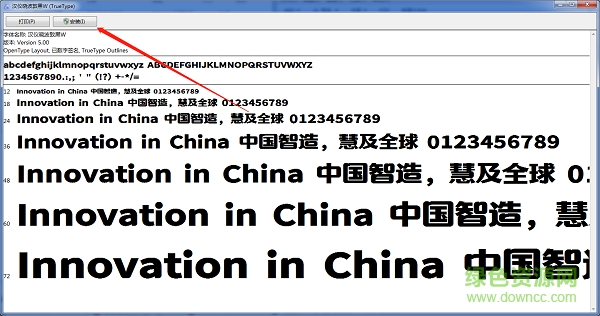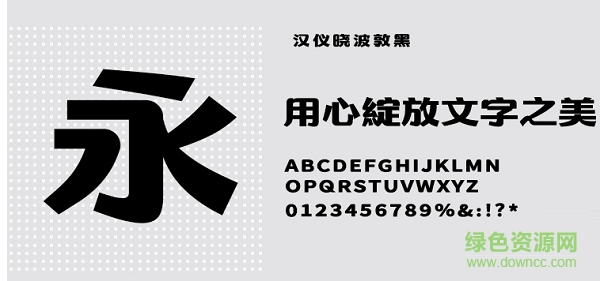
漢儀曉波敦黑w體
漢儀曉波敦黑字體免費(fèi)版是一款具有黑體字特色的字體,字體整體偏黑偏粗,簡(jiǎn)單分明的字體界面讓字體能顯現(xiàn)的更加的真實(shí)簡(jiǎn)單,非常實(shí)用與廣大的文學(xué)作品設(shè)計(jì)中,需要的用戶快來綠色資源網(wǎng)下載吧!
漢儀曉波敦黑體簡(jiǎn)介:
漢儀曉波敦黑字體是一款由漢儀字庫推出的基于常規(guī)黑體之上創(chuàng)作的標(biāo)題字,該字體汲取了黑體嚴(yán)肅而準(zhǔn)確的特征,又不失手寫的溫潤感,5:4的長寬比例使字體更顯穩(wěn)定,使用更美化!